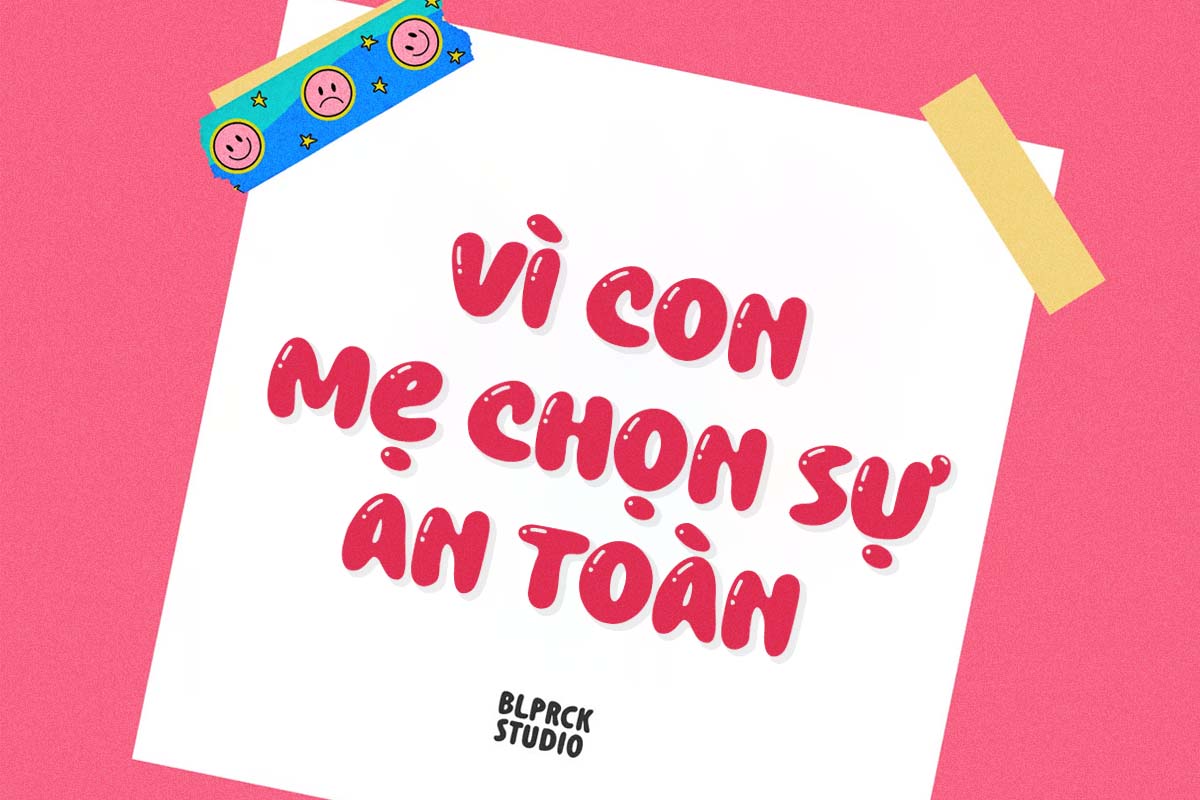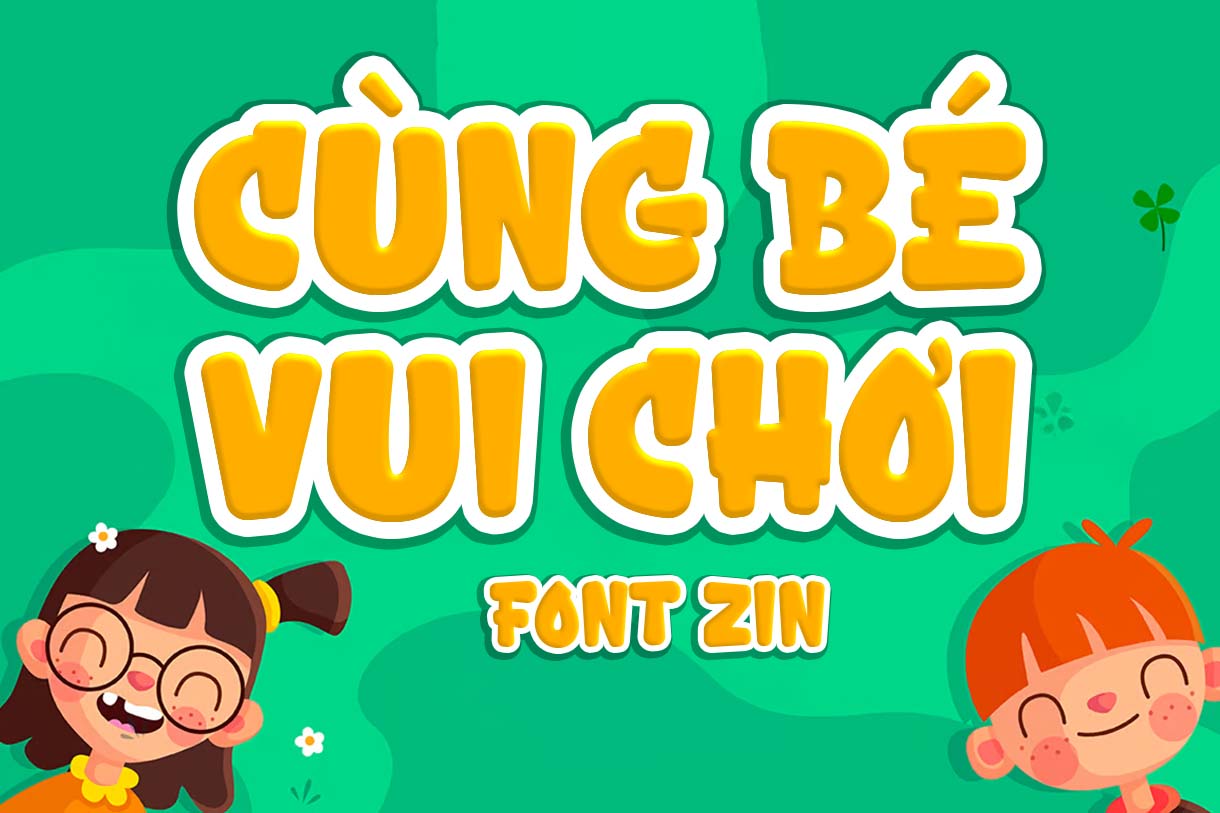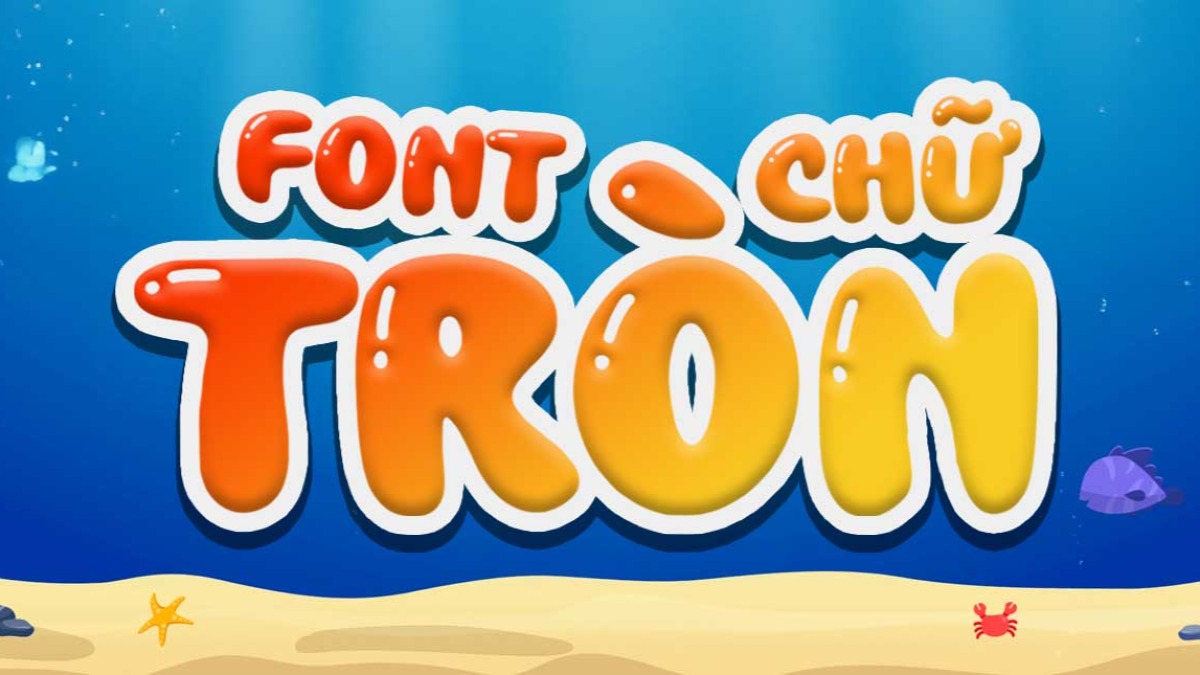
[Tải Xuống] Top 13 Font Chữ Tròn Việt Hóa Dễ Thương, Vui Nhộn Cho Thiết Kế
Tổng hợp 13 font chữ tròn Việt hóa đẹp, thân thiện và năng động, giúp thiết kế trở nên sinh động, đáng yêu và nổi bật trong mọi dự án sáng tạo.
Bạn đang tìm một font chữ tròn mang lại cảm giác thân thiện, vui tươi và đáng yêu cho thiết kế của mình?
Font chữ tròn Việt hóa (hay còn gọi là font chữ béo tròn) chính là lựa chọn hoàn hảo giúp tạo nên sự khác biệt, thu hút ánh nhìn của nhóm khách hàng trẻ em, gia đình, ẩm thực hoặc giải trí.
Với những đường nét bo cong mềm mại, dày dặn và sinh động, font chữ tròn giúp thiết kế của bạn trở nên gần gũi và bắt mắt hơn bao giờ hết.
Trong bài viết này, Fontdep.vn giới thiệu 13 font chữ tròn Việt hóa dễ thương, vui nhộn, được tuyển chọn kỹ lưỡng, hỗ trợ tiếng Việt hoàn chỉnh — sẵn sàng để bạn tải về và sử dụng cho mọi dự án sáng tạo.
Font Chữ Tròn Là Gì?
Font chữ tròn hay font chữ béo tròn là những kiểu chữ có nét bo cong, mềm mại ở mọi góc cạnh, tạo cảm giác thân thiện và tươi sáng.
Chúng thường thuộc nhóm Sans Serif hoặc Display, có độ dày nổi bật và hiệu ứng thị giác mạnh mẽ.
Đặc điểm nổi bật:
- Kiểu dáng thân thiện, dễ chịu khi nhìn.
- Độ dày cao, lý tưởng cho tiêu đề, logo, poster.
- Truyền tải cảm xúc vui tươi, gần gũi.
- Hỗ trợ tiếng Việt đầy đủ, hiển thị mượt mà trên mọi phần mềm thiết kế.
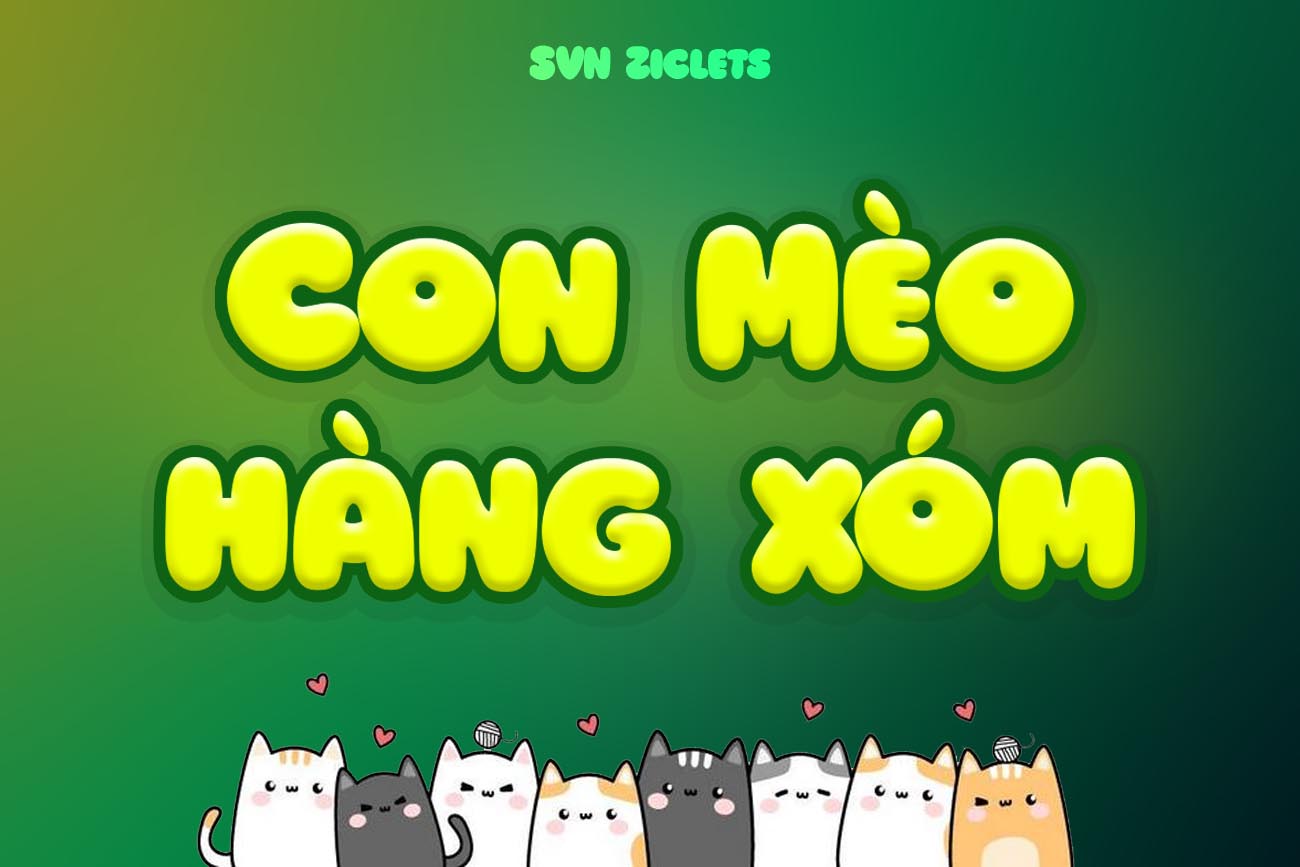
Ứng Dụng Nổi Bật Trong Thiết Kế
Font chữ tròn phát huy hiệu quả tuyệt vời trong các lĩnh vực cần sự tươi vui và thu hút:
- Thiết kế trẻ em: Logo mầm non, đồ chơi, truyện tranh.
- Ẩm thực & Đồ ăn vặt: Menu, bao bì bánh kẹo, thương hiệu ăn vặt.
- Marketing: Poster hoạt hình, banner quảng cáo, logo dí dỏm.
Danh Sách TOP 13 Font Chữ Tròn Việt Hóa Đáng Yêu
1. Font iCiel Pony Việt Hóa – Đáng Yêu, Hoạt Hình (Miễn Phí)
iCiel Pony mang phong cách hoạt hình ngộ nghĩnh, với đường nét tròn đầy và mềm mại. Font tạo cảm giác vui tươi, thân thiện, lý tưởng cho poster, logo hoặc các thiết kế sáng tạo. Việt hóa hoàn chỉnh, hiển thị tiếng Việt mượt mà.
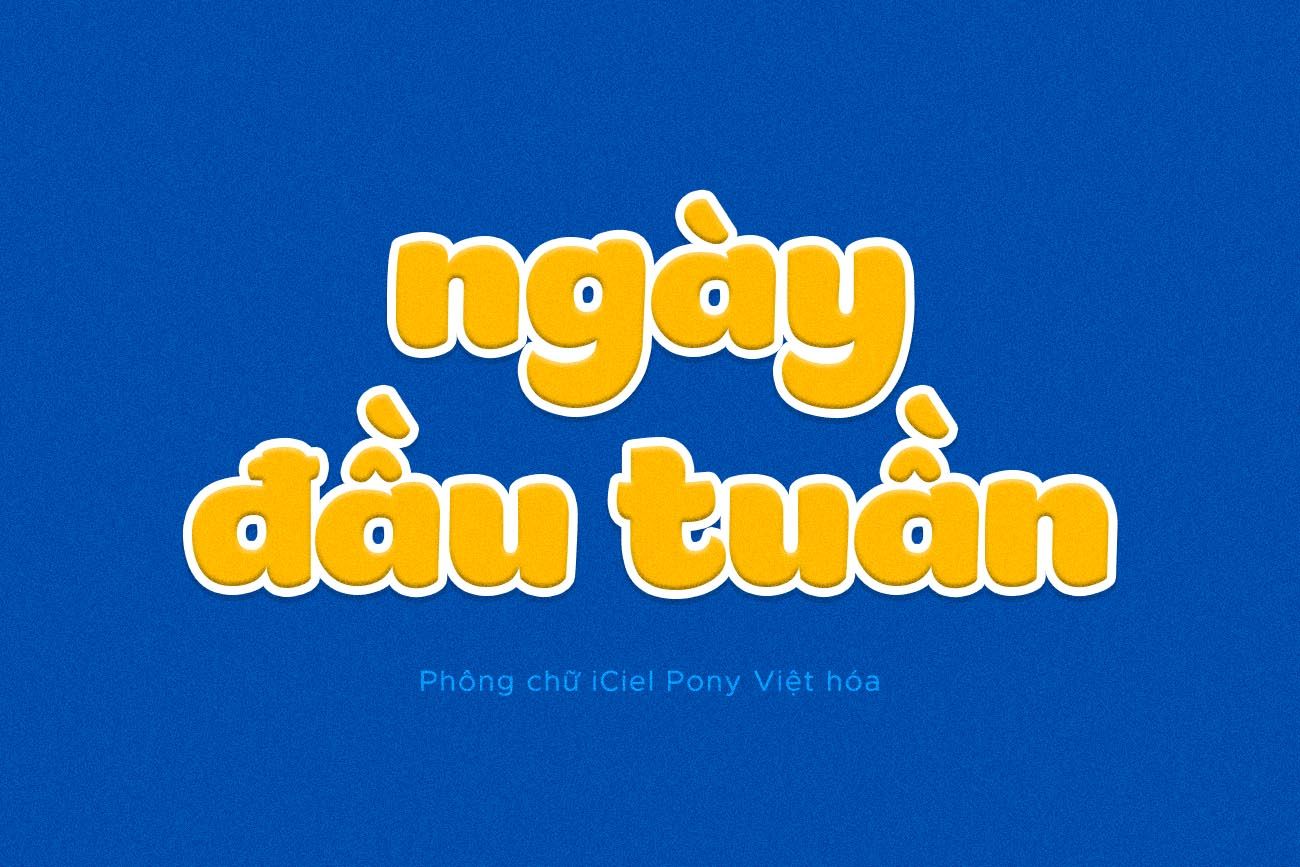
2. Font iCiel Cadena Việt Hóa – Sáng Tạo, Ấn Tượng (Miễn Phí)
iCiel Cadena có cấu trúc béo tròn và bo cong mượt mà, gợi cảm giác ngọt ngào và thân thiện. Font phù hợp cho bao bì, poster, logo hoặc tiêu đề thiết kế trẻ trung. Việt hóa đầy đủ, hiển thị rõ nét tiếng Việt.
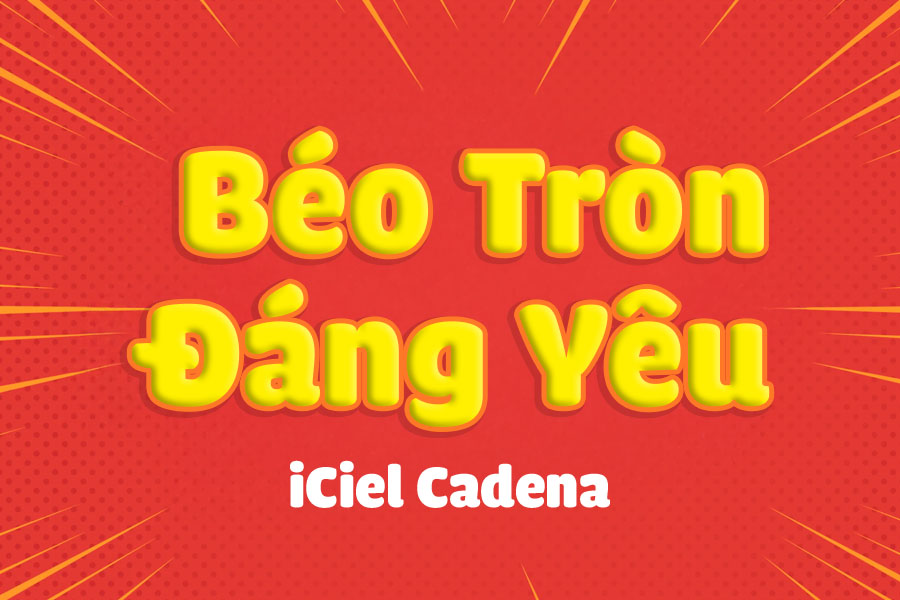
3. Font SVN Ziclets Việt Hóa – Béo Tròn, Tinh Nghịch (Miễn Phí)
SVN Ziclets mang phong cách hoạt hình vui nhộn, với các ký tự tròn trịa như được vẽ tay. Font thể hiện năng lượng trẻ thơ, lý tưởng cho thiết kế đồ chơi, poster thiếu nhi hoặc truyện tranh. Việt hóa chuẩn, tương thích hoàn hảo.
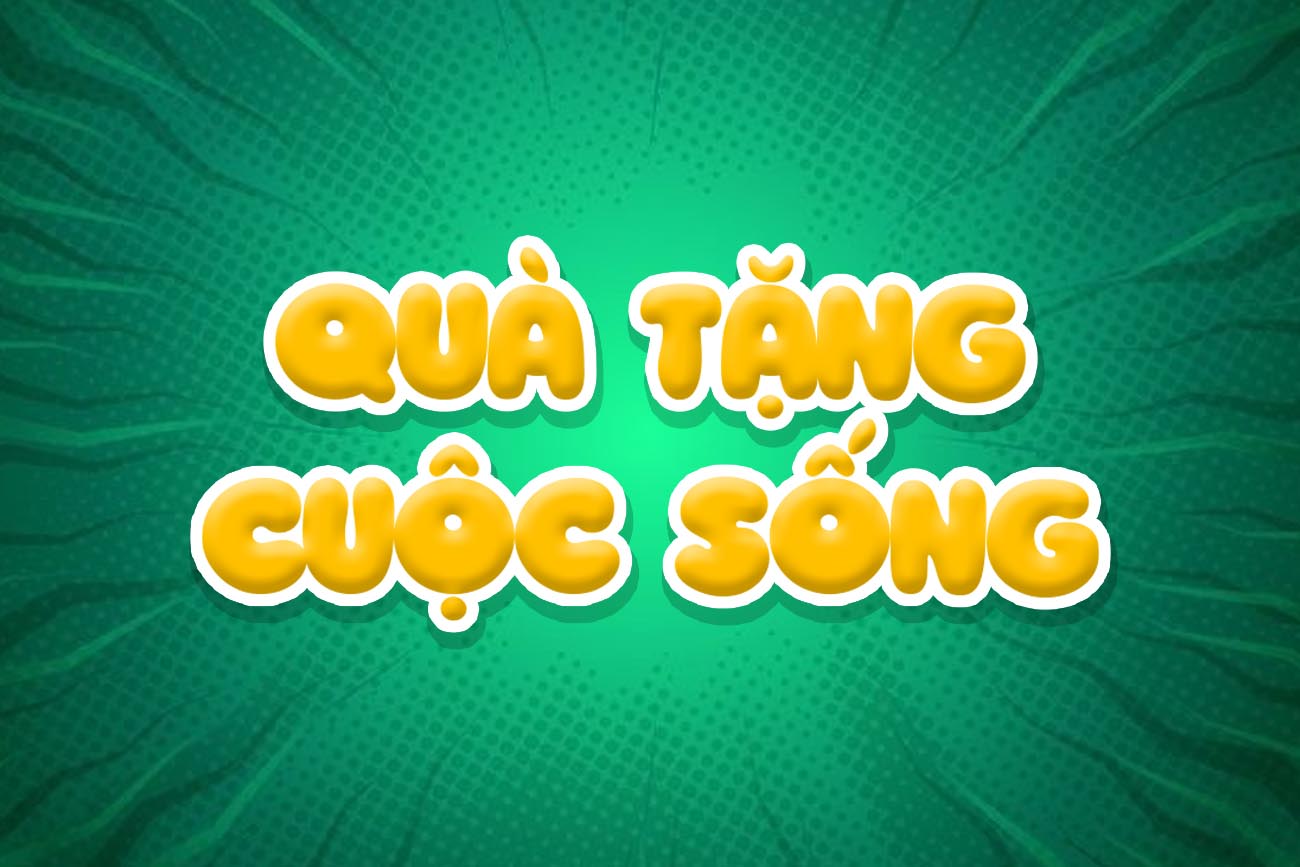
4. Font TH Tijuf Regular Việt Hóa – Hoạt Hình, Mạnh Mẽ
TH Tijuf Regular có đường nét tròn dày, cân đối giữa mềm mại và mạnh mẽ. Font lý tưởng cho tiêu đề, logo hoặc poster chủ đề hoạt hình. Việt hóa đầy đủ, hiển thị rõ ràng, đẹp mắt.
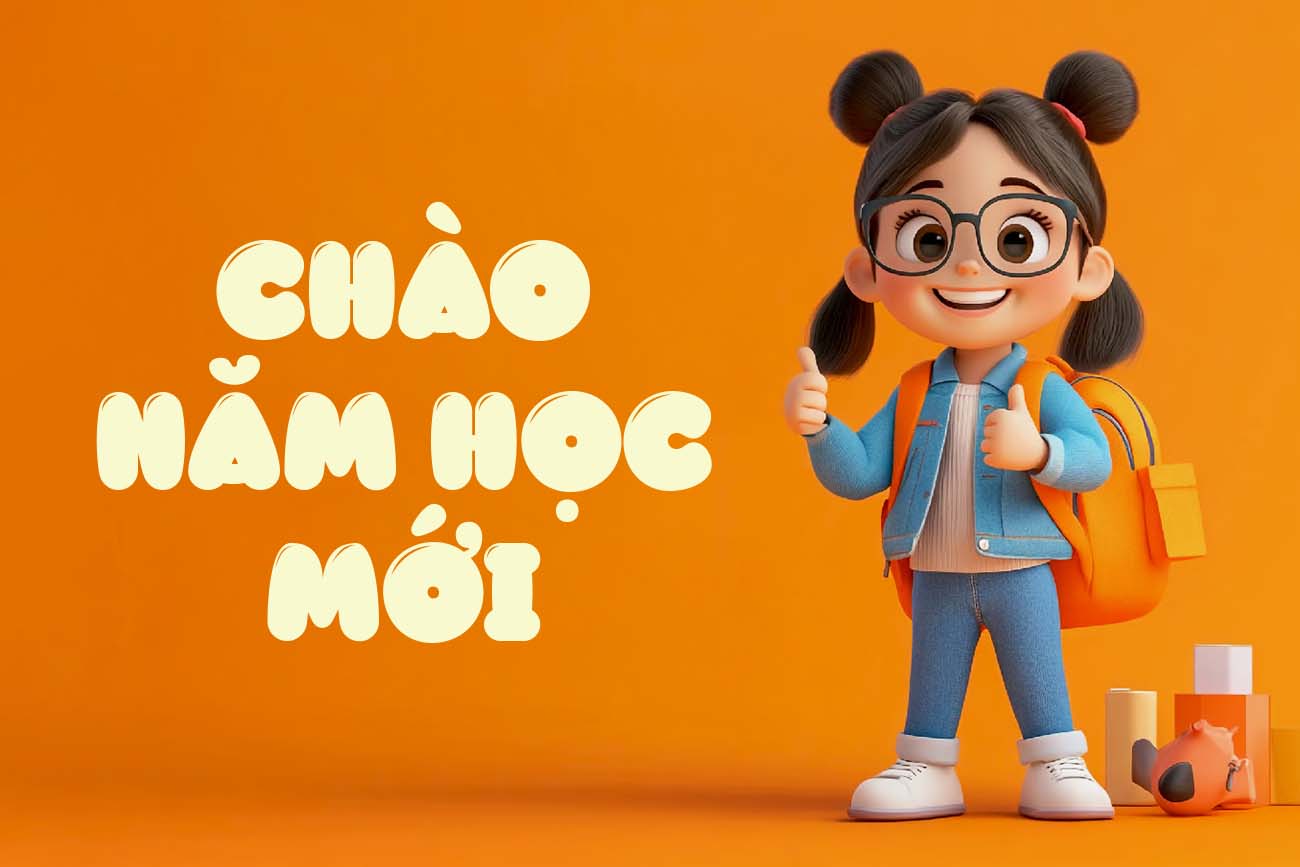
5. Font SVN Hublot Việt Hóa – Vui Nhộn, Đáng Yêu (Miễn Phí)
SVN Hublot là font sans-serif bo tròn, mềm mại, đậm chất hoạt hình. Mang lại cảm giác thân thiện, dễ thương, rất hợp với thiết kế trẻ em, sticker hoặc poster vui tươi. Việt hóa chuẩn, dùng tốt trên mọi nền tảng.
- Việt hóa bởi: Team SVN
6. Font TH Ekamai Việt Hóa – Tròn Trịa, Thân Thiện
TH Ekamai mang phong cách brush tròn trịa, mềm mại, dễ thương và gần gũi. Rất phù hợp cho thiết kế mang tính cảm xúc hoặc hướng đến trẻ nhỏ. Việt hóa đầy đủ, hiển thị mượt mà mọi dấu tiếng Việt.
- Tác giả gốc: Schizotype
- Việt hóa bởi: Font TH
7. Font TH Choret Fudyng Việt Hóa – Bubble Tinh Nghịch
TH Choret Fudyng là font kiểu bong bóng (bubble) với hình khối căng tròn, đáng yêu và nổi bật. Rất phù hợp cho game, poster, hoặc sản phẩm đồ ăn nhanh. Việt hóa chuẩn Unicode, hiển thị rõ nét.
- Tác giả gốc: Alit Sua Negara (Alit Design Studio)
- Việt hóa bởi: Font TH
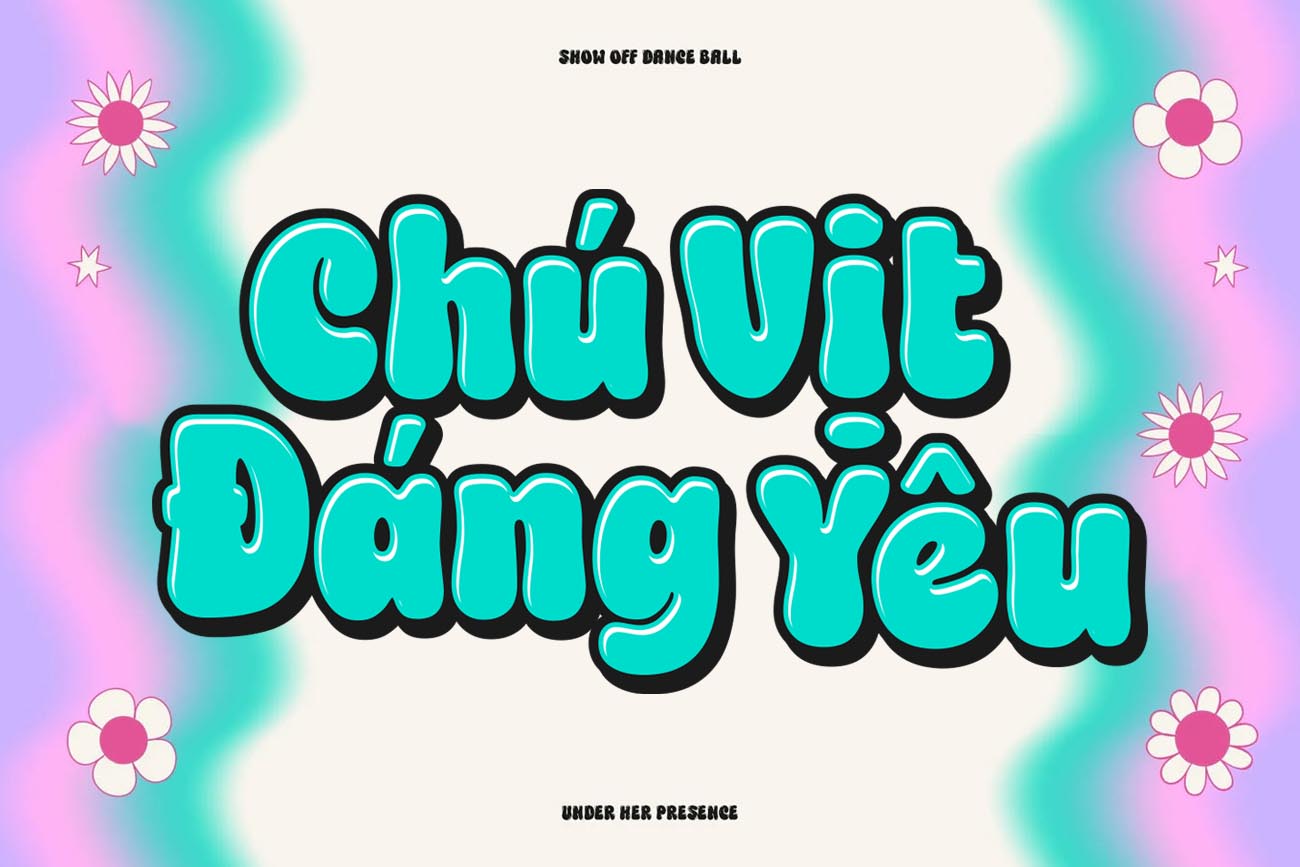
8. Font TH Super Dessert Việt Hóa – Mập Mạp, Ngọt Ngào
TH Super Dessert lấy cảm hứng từ bánh kẹo hoạt hình, với nét chữ dày và bo tròn dễ thương. Font rất hợp cho bao bì, poster hoặc menu đồ ăn vặt. Việt hóa đầy đủ, hỗ trợ tiếng Việt hoàn chỉnh.
Kết Luận
Font chữ là “ngôn ngữ cảm xúc” của thiết kế. Với 13 font chữ tròn Việt hóa trong bộ sưu tập này, bạn đã có trong tay công cụ hoàn hảo để tạo nên những ấn phẩm đáng yêu, gần gũi và đầy năng lượng tích cực.
Dù bạn thiết kế logo đồ ăn, poster hoạt hình hay bìa truyện thiếu nhi, các font béo tròn này sẽ giúp thông điệp của bạn trở nên sinh động và thu hút ngay từ ánh nhìn đầu tiên.